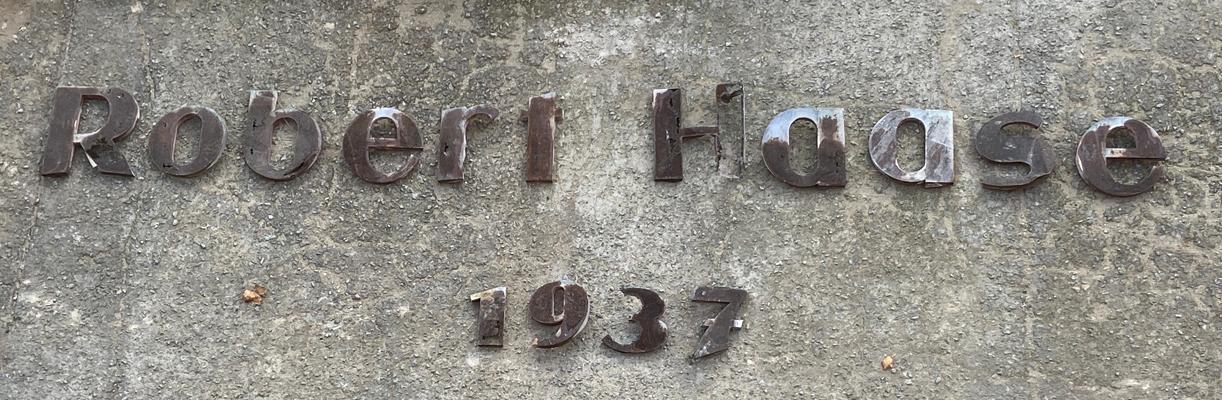
Suche den Namen/Schrifttyp des ehemaligen Schriftzuges an meine Hauswand
ich suche den Namen bzw. Bezeichnung des auf dem Foto abgeildeten Schriftzuges und der Ziffern.
Beides zierte meine Hauswand und soll in abgeänderter Form (Haase - Speicher 1937 / 2017) wieder montiert werden.
Hierfür benötige ich das Schrifttypenbild für die zu ergänzenden Buchstaben.
Von wan ist denn die Beschilderung? Aus den 1930ern? Wenn ja: Benannte Schriften waren zu dieser Zeit Druckschriften (aus Blei oder Holz). Damit konnte man nur drucken. Schilder waren Spezialanfertigungen verschiedener Betriebe. Insofern ist die Chance gering, eine passende Schrift zu finden. Ein Schriftgestalter könnte die fehlenden Buchstaben aber passend zu den vorhandenen entwerfen.
Wen die Beschilderung deutlich jünger wäre, könnte man nochmal überlegen.
Ich bin keiner derjenigen hier, die Ahnung davon haben, aber für mich sieht das handgemacht aus. Ist das Holz?
Falls sich keiner mehr meldet, frag mal bei @catfonts an, der hat viel Erfahrung damit, aus Gebäudebeschriftungen Schriften oder Ergänzungen zu entwickeln.
Ja, ist aus den 30igern und aus Blech.
Exakt diese Schrift wird man wahrscheinlich nicht finden. Ich habe aber das Gefühl, dass die Schrift auf einer Satzschrift basieren könnte. Für die Umsetzung wurden vom Schildermacher sicher Details angepasst aber die Schildermacher haben sich auch hier und da an Vorlagen orientiert. Insofern könnte man schon noch einmal nach ähnlichen Satzschriften aus den 1920er und 1930er Jahren recherchieren.